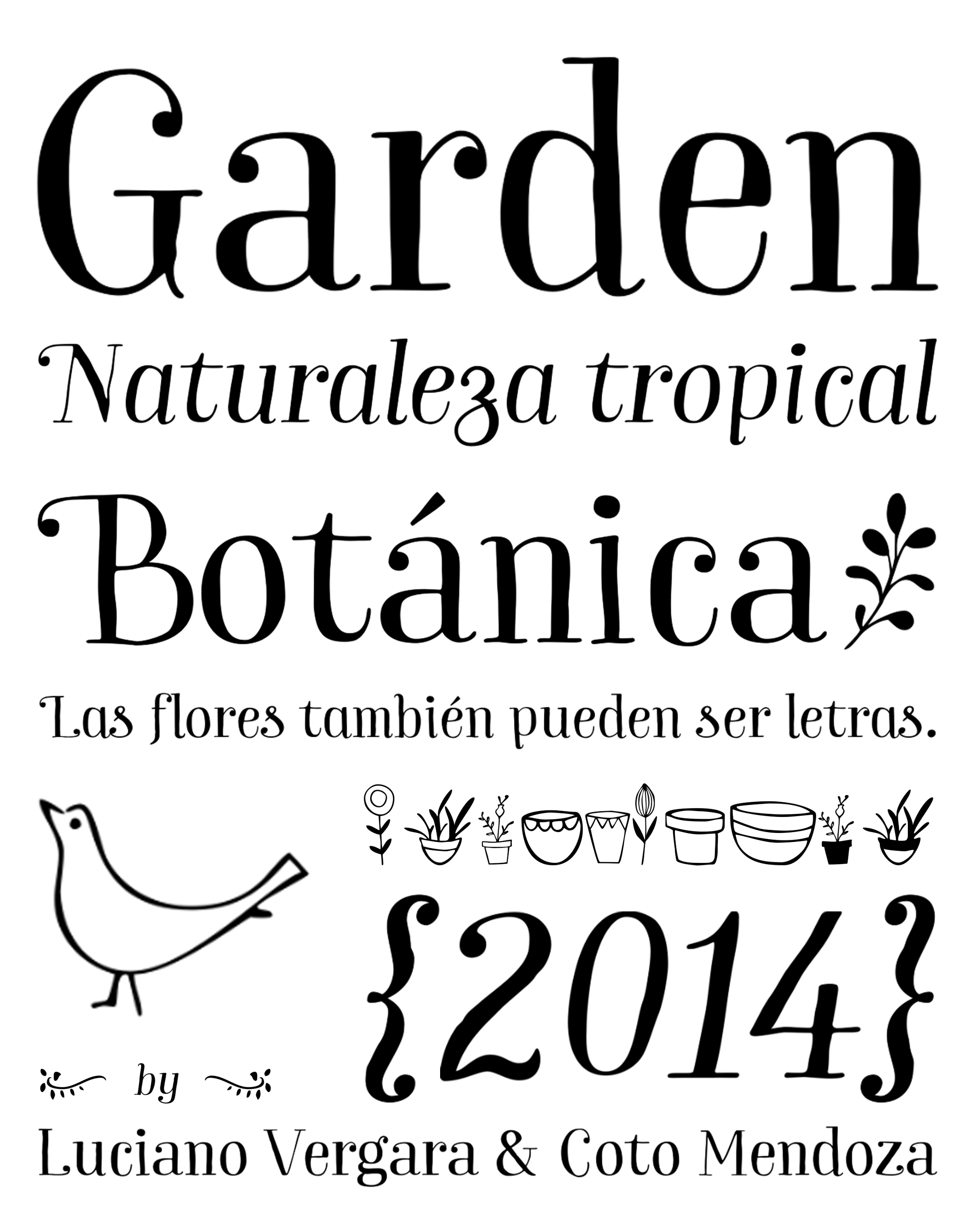
| Créditos | Luciano Vergara, Coto Mendoza |
| Descripción | El año pasado visitamos Brasil y quedamos totalmente cautivados por su gente alegre y cálida. Su naturaleza salvaje es absolutamente asombrosa y muy perceptible tanto en la impresión textil como en el diseño floral. Eso fue precisamente lo que nos inspiró para crear algunos ornamentos y dingbats, que luego convertimos en una única obra tipográfica. El tipo de letra resultante se llamó |
| Clasificación | Títulos, Dingbats |
| Familia(s) | Essential, Essential Italic, Essential Alt, Essential Alt Italic, Swash, Swash Italic, Swash Alt, Swash Alt Italic, Ornaments, Dingbats |